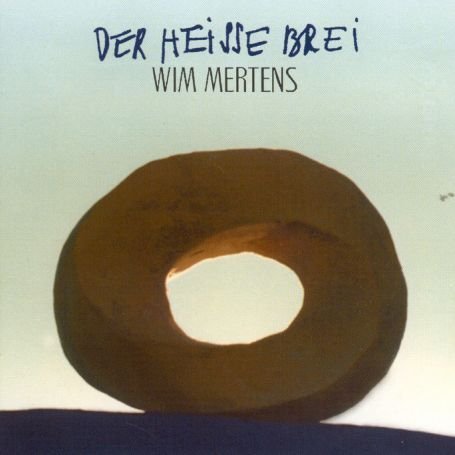
bräuchte für eine Beschreibung in einer Studienarbeit die Schriftnamen,
von den Schriften die auf dem CD-Cover von "Der heiße Brei" (Wim Mertens) verwendet
wurden.
Kennt sich jemand so gut aus und kann mir weiter helfen?
"Der heiße Brei" ist handgeschrieben. Alles verschiedene Buchstabenformen.
...ja stimmt...auf der Rückseite der CD sind die Songtitel auch in der Handschrift geschrieben und die Buchstaben sehen immer unterschiedlich aus.
Jetzt wäre die "Untere" wirklich noch spannend! (und hilfreich)
Das "Wim Mertens" sieht der Schrift Myriad Light Condensed sehr ähnlich...ist es aber nicht :-(
Leider komme ich nicht weiter....
Kommt vielleicht jetzt jemand drauf?